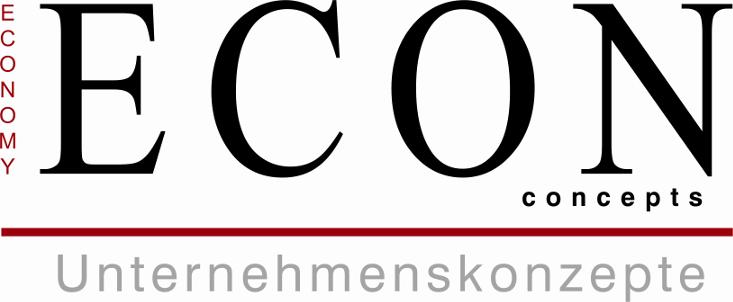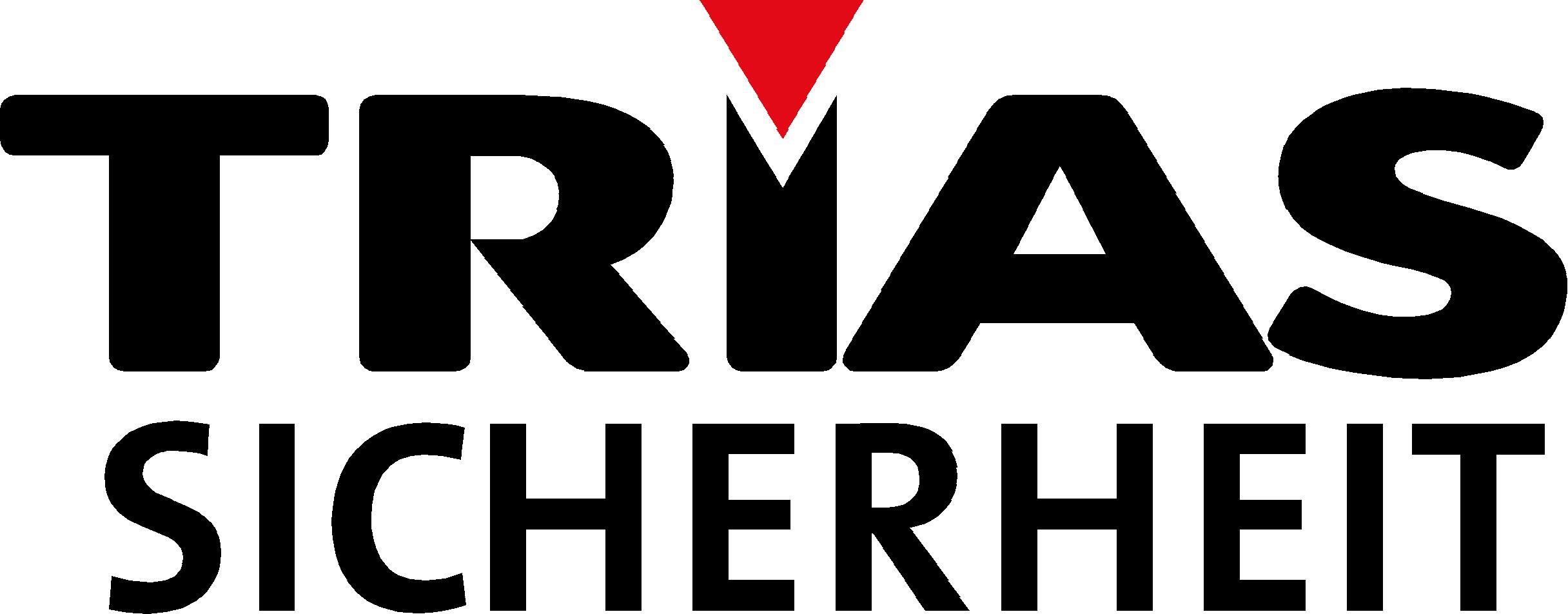
Welche Schriftart ist das ?
Hallo,  wäre jemand so lieb mir mitzuteilen um welche Schriftarten es sich hierbei bei diesen beiden Bildern handelt ?
ECON ist eine gequetschte Times.
Unternehmenskonzepte ist eine Helvetica.
SICHERHEIT ist The Sans Bold.